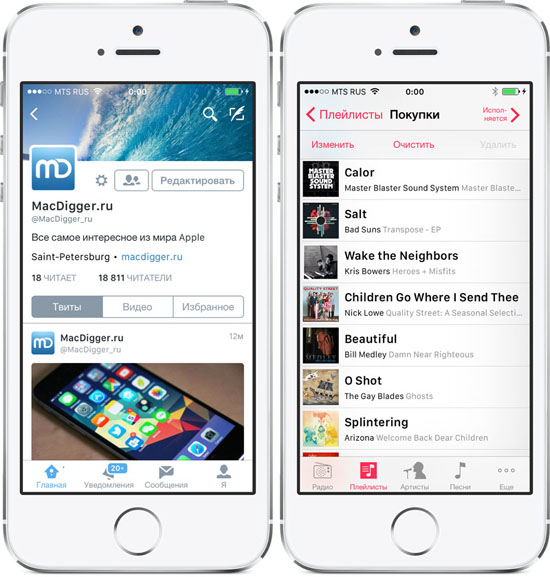
Как установить шрифт из Apple Watch на iPhone и iPad, не дожидаясь iOS 9
Не секрет, что специально для «умных» часов Apple Watch компания Apple создала шрифт, при помощи которого демонстрируются уведомления на экране новинки. Сегодня стало известно о намерении производителя перенести его в iOS 9 и OS X 10.11.
Шрифт называется San Francisco Display и имеет девять вариантов оформления с разной насыщенностью. В настоящее время он используется только на смарт-часах и клавиатуре 12-дюймового MacBook, однако с выходом новых программных платформ появится также на iPhone, iPad и Mac.